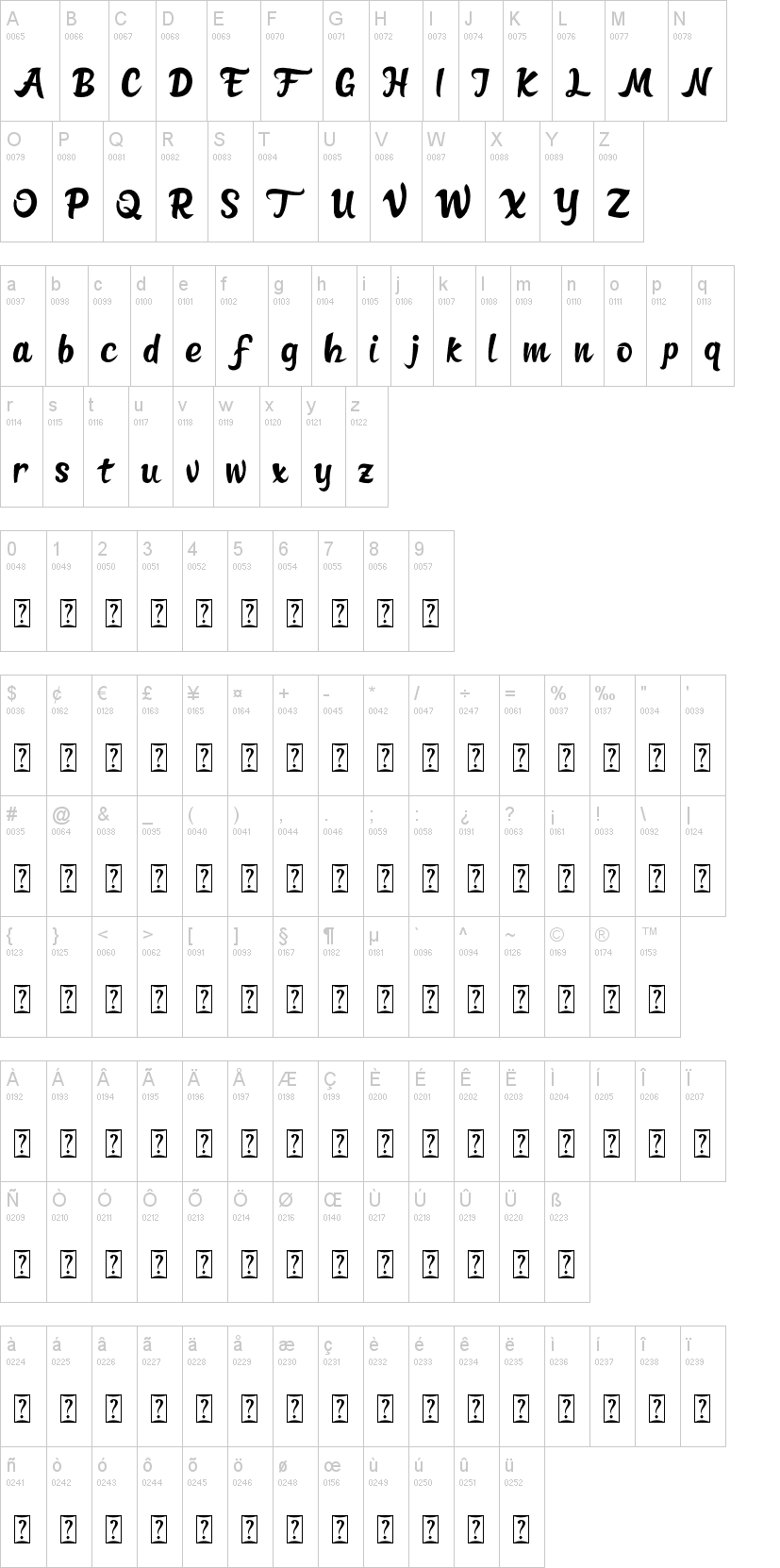
Frederico
Frederico 是一种优雅的手写风格字体,设计师Millo Salgado于2018年创建了这款字体。Frederico 字体的特点是其流畅、优美的笔画和现代感,同时也具有一定的传统感。它适用于各种设计场景,如品牌标识、海报、包装设计等。Frederico 字体的字形非常清晰,易于阅读,同时也非常适合用于大字体设计,让设计作品更加突出。
Frederico是一款非常不错的手写艺术字体,具有很好的视觉感,适合于文化类的宣传设计、商业类品牌的广告和产品包装设计以及个性化文字排版等较多场景。